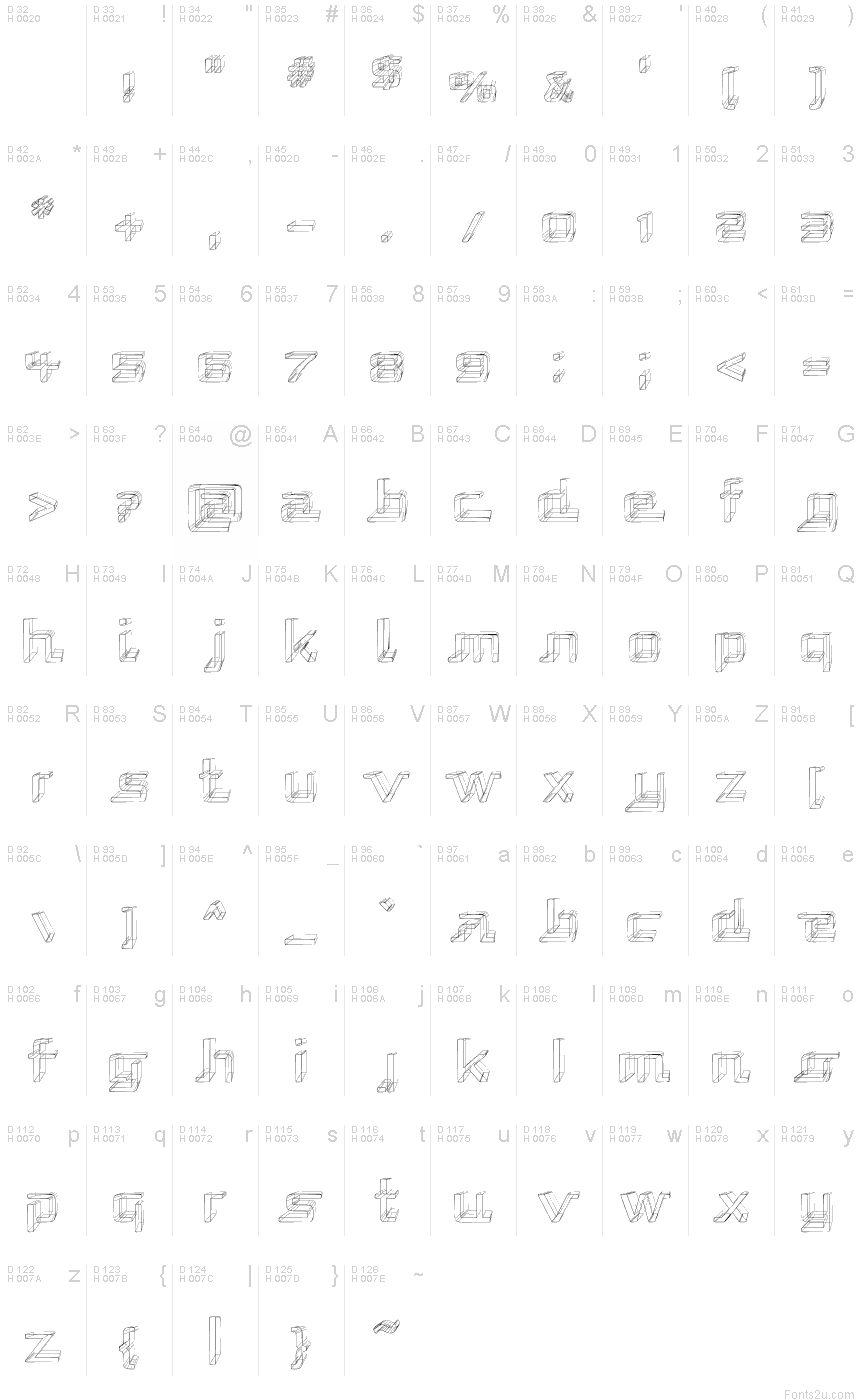
Republika - Sketch
由 Apostrophe 设计的 Republika Sketch 是一款免费的 3D 科技风显示字体,其灵感源自草图,仿佛是将概念设计草图直接转化为字形。字母采用开放式线框轮廓、锐利转角和圆润的内弧线,营造出一种轻盈且具有未来感的节奏,流露出建筑设计般的构思,而非平滑的处理。
它非常适合用于海报标题、专辑封面、游戏图形、活动传单以及动态标题卡,这款免费字体能在不显沉重的前提下,带来浓郁的科幻或原型感氛围。由于字形仿佛是空间中绘制的对象,它也适用于短标题、LOGO 设计实验,以及需要手绘技术感的界面风格品牌设计。